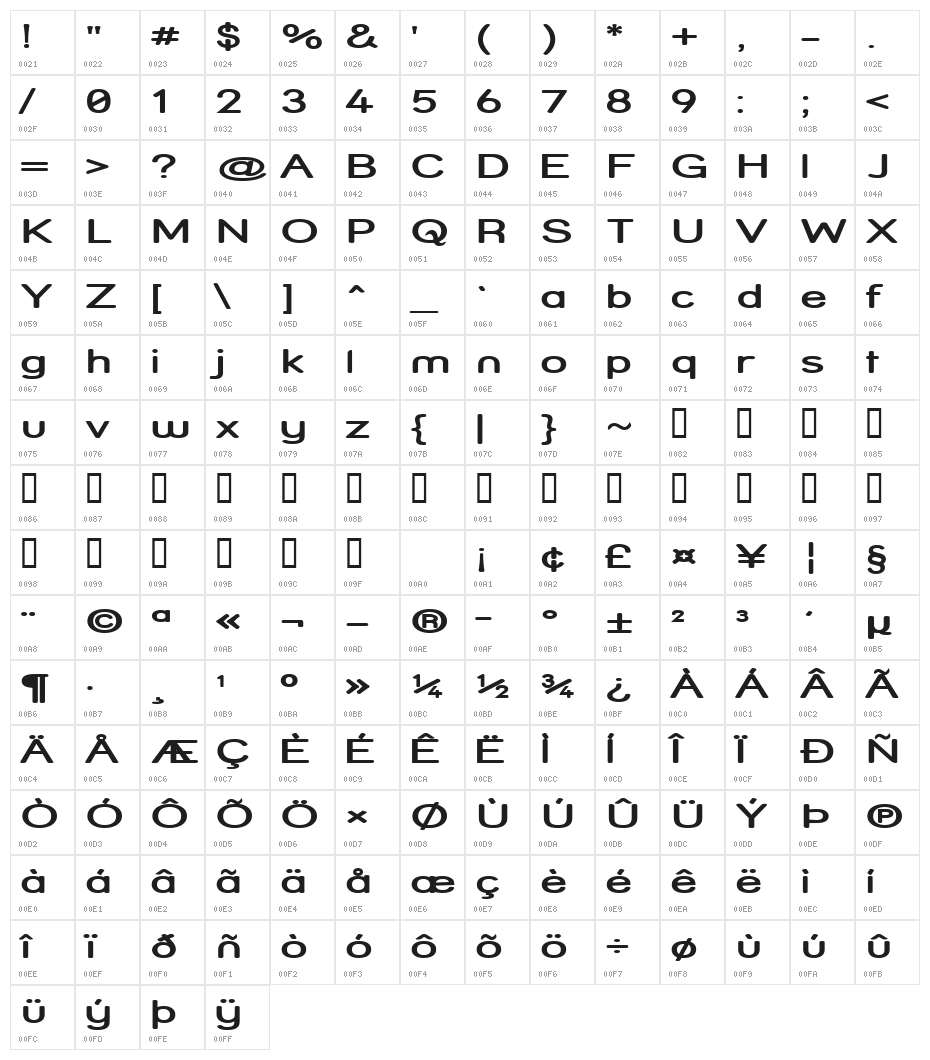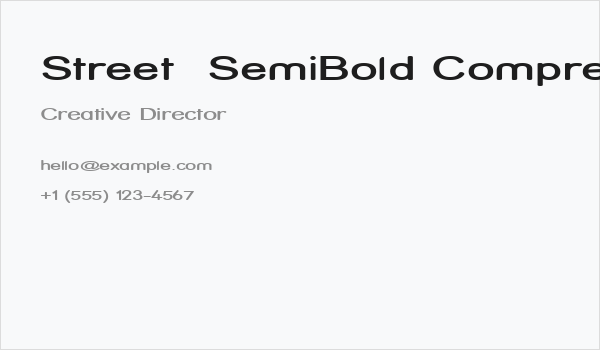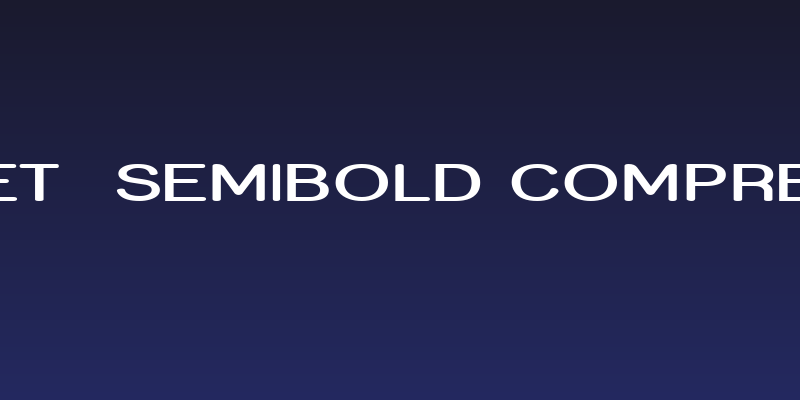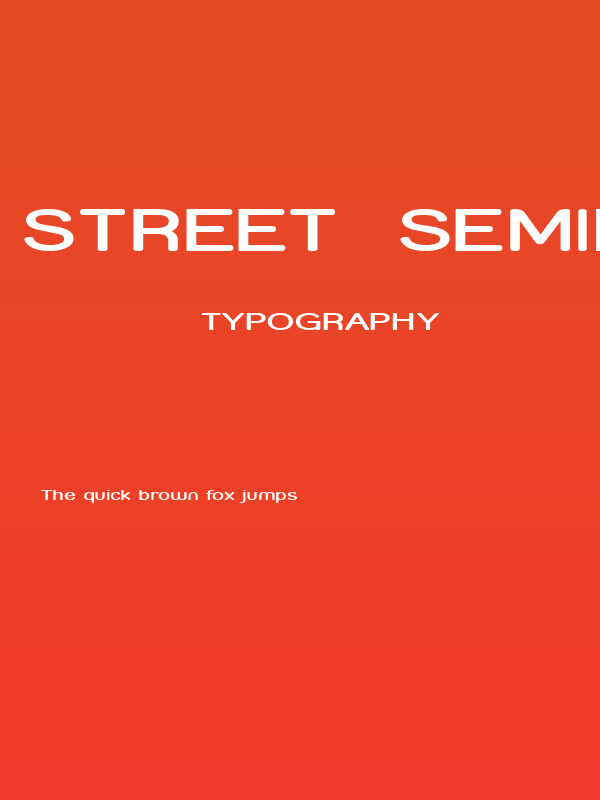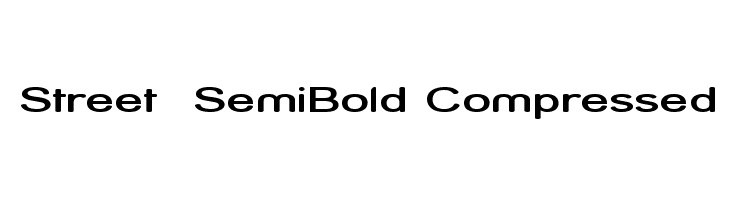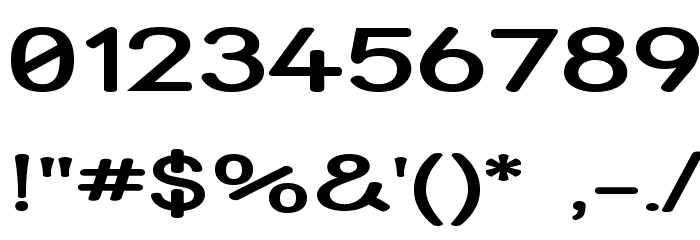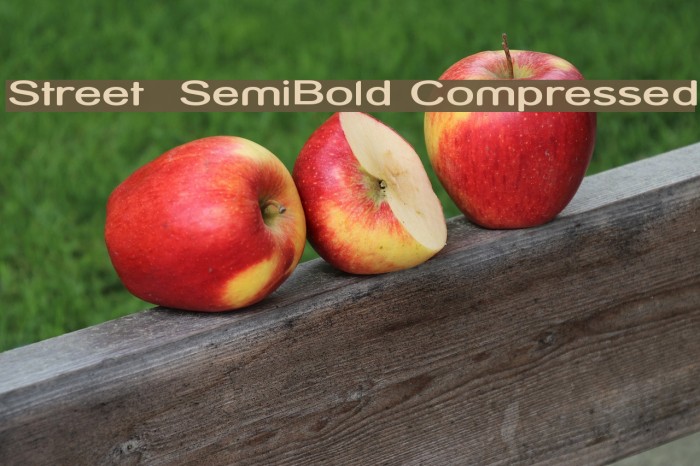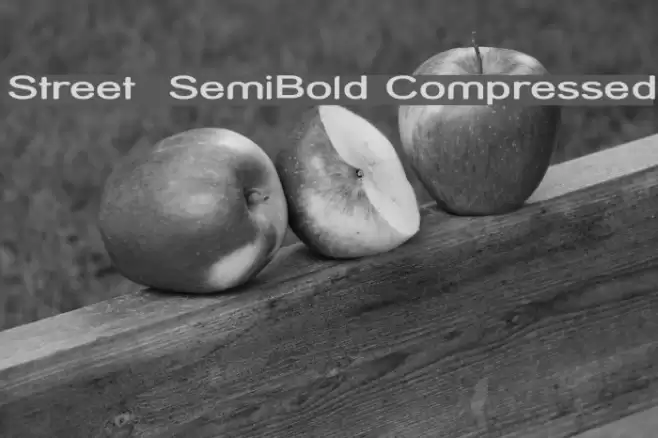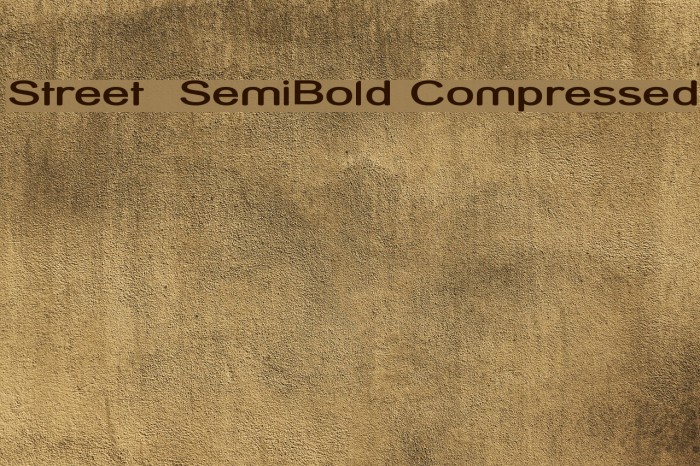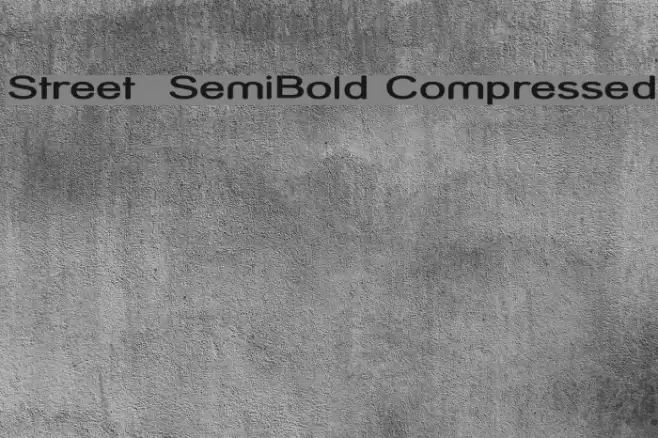
Street SemiBold Compressed Font
✎ Sans Serif
| Категория | Sans Serif |
| Область применения | Headlines, Logos, Digital Interfaces |
| Рекомендуемые проекты | Ideal for branding, advertising, and digital interfaces where space is limited but clarity is essential. |